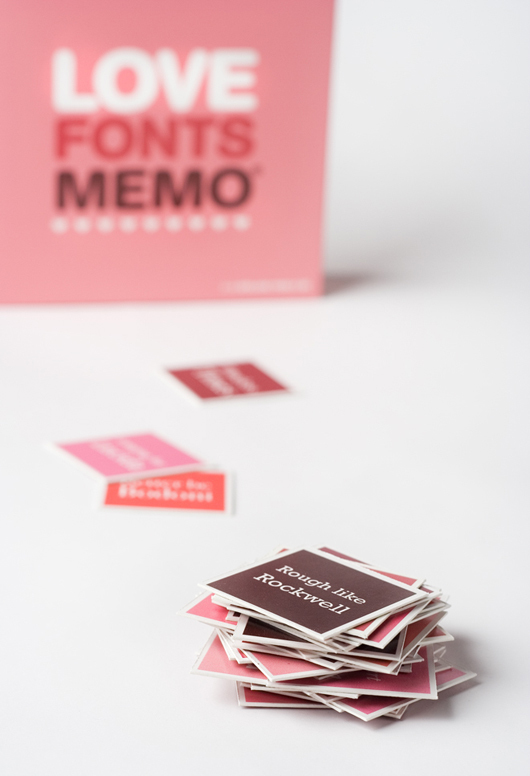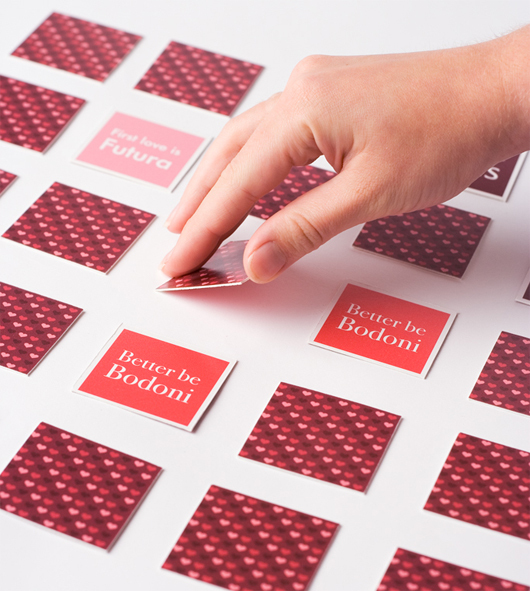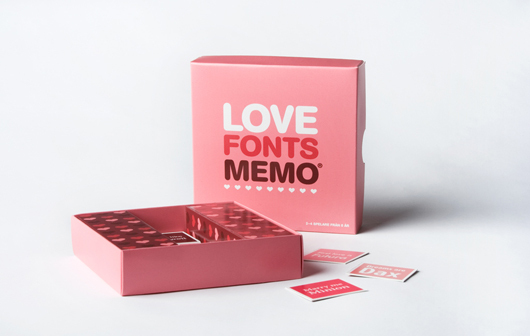
Love Fonts Memo, un juego de adivinar parejas de tipografías
Hay una cosa en la vida que es muy muy adictiva. No hablamos de clásicos vicios como el tabaco, el café, o las pastillas de la tos. Este vicio es algo que ha tenido a más de uno/a enganchadísimo/a. Hasta tal punto de ser un virus que invade a una masa de personas que automáticamente se convierten en unos…adictos. ¿Y cuál es este vicio? ¡Los juegos de adivinar parejas!
Inventia ha sentido debilidad por estos «jueguecitos» a lo largo de los años y es algo que le ocurre a más de uno/a. Pero lo peor de todo, es que este vicio puede convertirse en algo serio, si vemos lo que ha creado Sara Strand para entretenernos.
Esta diseñadora e ilustradora de Estocolmo, es la autora de Love Fonts Memo, un clásico juego de memoria, donde se tienen que adivinar parejas…¡de tipografías! Una maravilla para los diseñadores que quieran entrenar su «ojo» y también muy apto para los amantes del diseño gráfico y la tipografía.
Pero la gracia del juego no reside en su mecánica, que es muy sencilla, sino en lo coquetas y bien diseñadas que están las tarjetas. Y es que estas últimas representan las historias de amor entre las diferentes tipografías.
¿Quién se anima a jugar?